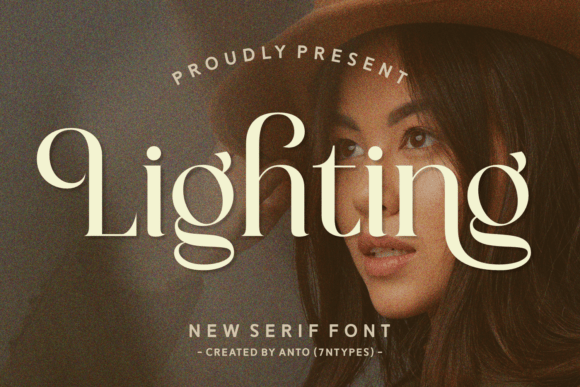
Lighting
์˜ฌ๋ฐ”๋ฅธ ๋””์ž์ธ ์š”์†Œ๋ฅผ ์ฐพ๋Š” ๊ฒƒ์€ ์–ด๋ ค์šธ ์ˆ˜ ์žˆ์ง€๋งŒ Lighting๋Š” ์ž‘์—…์„ ์ฆ‰์‹œ ํ–ฅ์ƒ์‹œํ‚ค๋Š” ๋›ฐ์–ด๋‚œ ์ปฌ๋ ‰์…˜์„ ์ œ๊ณตํ•ฉ๋‹ˆ๋‹ค.
์ •๋ฐ€ํ•˜๊ฒŒ ์ œ์ž‘๋œ Lighting๋Š” ๊น”๋”ํ•œ ๋ฒกํ„ฐ, ๋ถ€๋“œ๋Ÿฌ์šด ํƒ€์ดํฌ๊ทธ๋ž˜ํ”ผ ๋ฐ ์•ˆ์‹ฌํ•  ์ˆ˜ ์žˆ๋Š” ์ƒ์—…์šฉ ๋ผ์ด์„ ์Šค๋ฅผ ์ œ๊ณตํ•ฉ๋‹ˆ๋‹ค.
POD(์ฃผ๋ฌธํ˜• ์ธ์‡„) ์ œํ’ˆ, ๊ฒฐํ˜ผ์‹ ์ดˆ๋Œ€์žฅ ๋˜๋Š” ์†Œ์…œ ๋ฏธ๋””์–ด ๊ทธ๋ž˜ํ”ฝ์„ ๋งŒ๋“ค ๋•Œ Lighting๋Š” ์ด์ƒ์ ์ธ ์„ ํƒ์ž…๋‹ˆ๋‹ค.